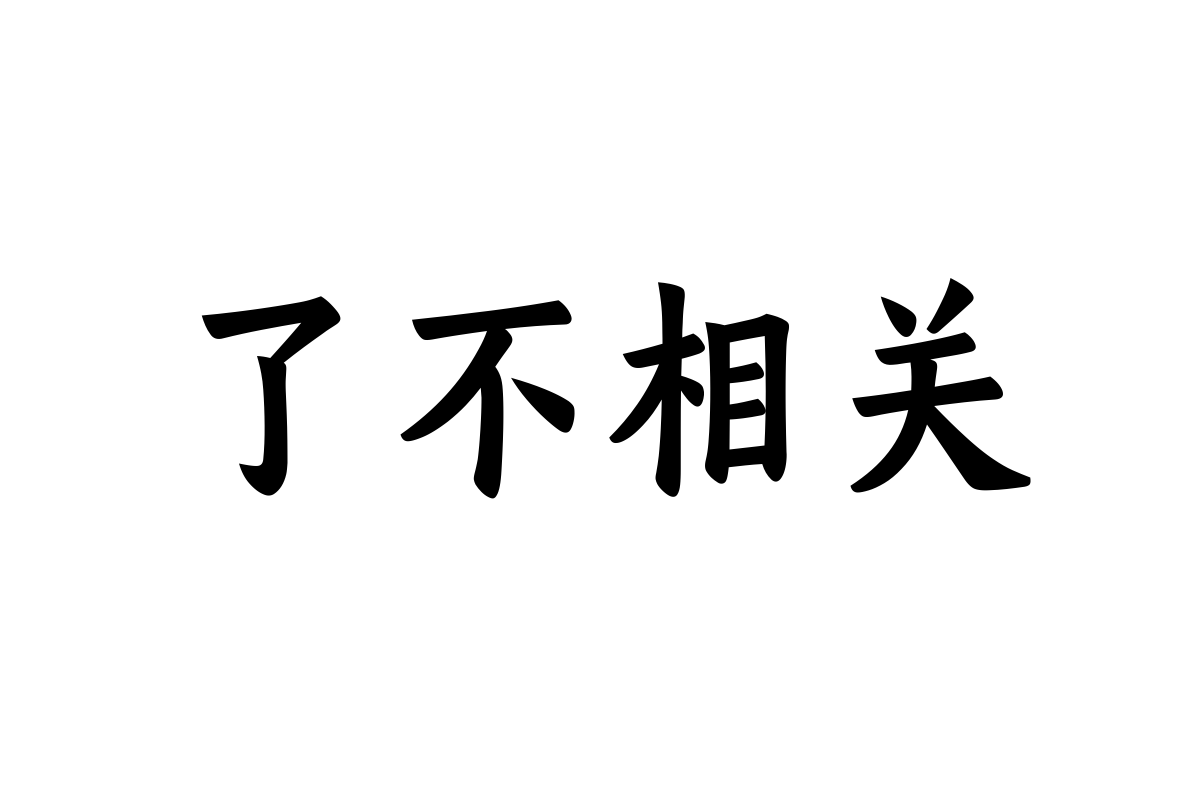
汉仪楷75w是一款现代中文字体,由汉仪字库出品。这款字体具有优雅、简洁的设计风格,适用于各种商业、广告、设计等领域。它具有75种不同的字形和风格,可以满足不同用户的需求。
汉仪楷75w字体的特点:
1. 优雅:汉仪楷75w字体线条流畅,字形优美,给人一种高雅的感觉。
2. 简洁:字体结构简单,笔画清晰,易于阅读和书写。
3. 适应性强:无论是在正式场合还是在非正式场合,汉仪楷75w字体都能展现出良好的效果。
4. 可定制:用户可以根据自己的需求对字体进行个性化定制,如修改字形、调整笔画粗细等。
总之,汉仪楷75w字体是一款适合各种应用场景的现代中文字体,无论是在设计还是印刷领域都能发挥出良好的效果。